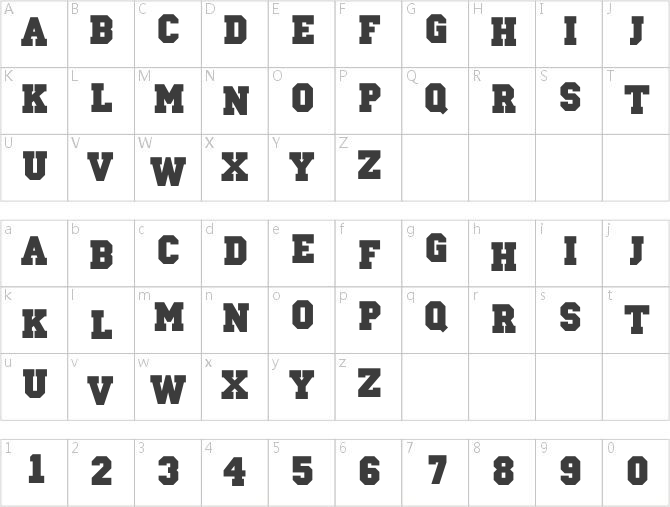
a_Campus-Bold
a_Campus-Bold介紹
a_Campus-Bold字體字庫(kù)是一款讓人賞心悅目、百看不厭的英文字體,適合各類(lèi)廣告和產(chǎn)品包裝設(shè)計(jì)應(yīng)用,字體大小0.02MB,格式為ttf字體,上傳用戶(hù)是東情,作者/版權(quán)方為未知